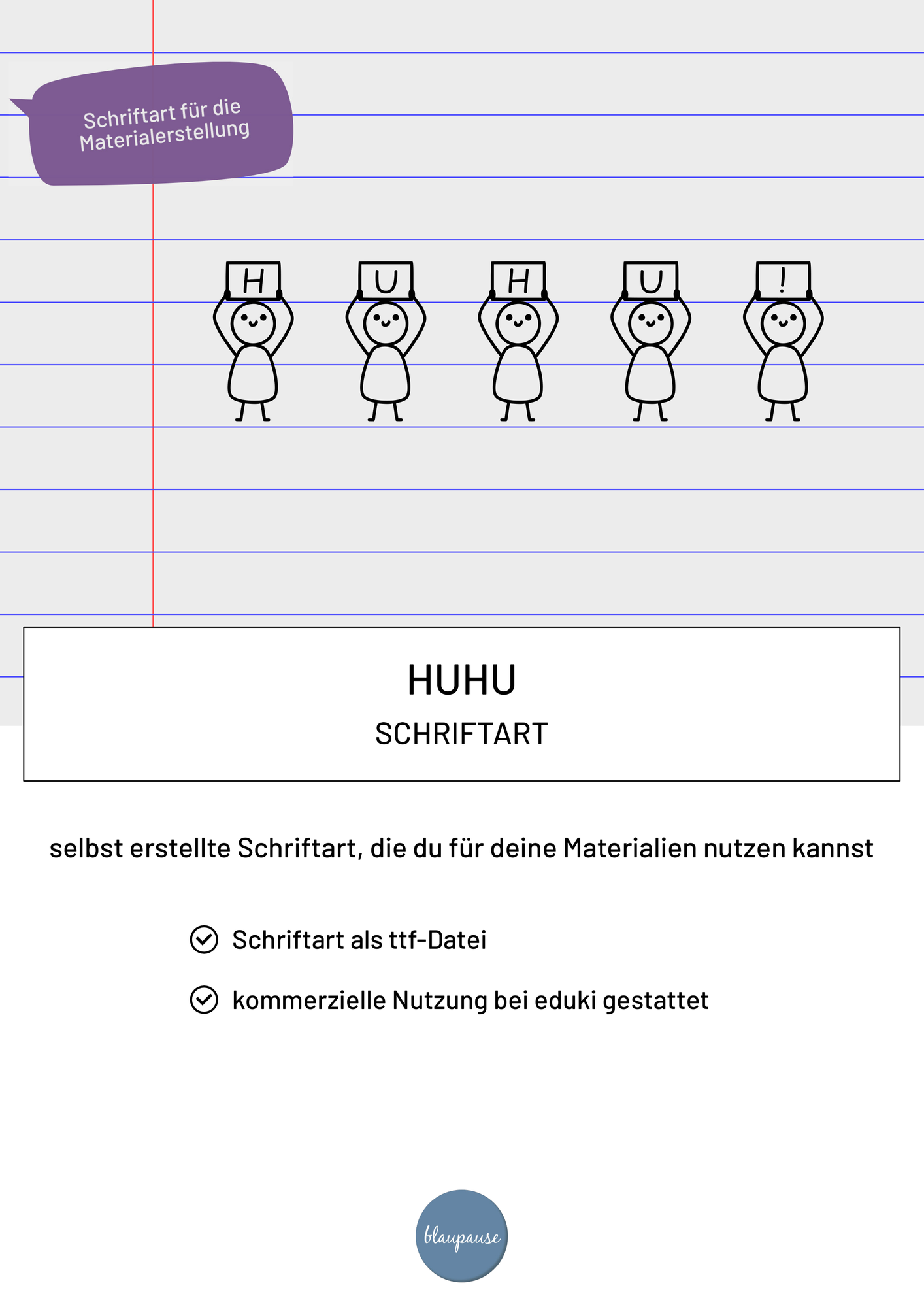
HUHU eignet sich besonders gut für Überschriften. Enthalten sind alle Großbuchstaben sowie alle Ziffern und zwei Sonderzeichen (! + ?). Viel Spaß damit!
HUHU - Schriftart | FREEBIE